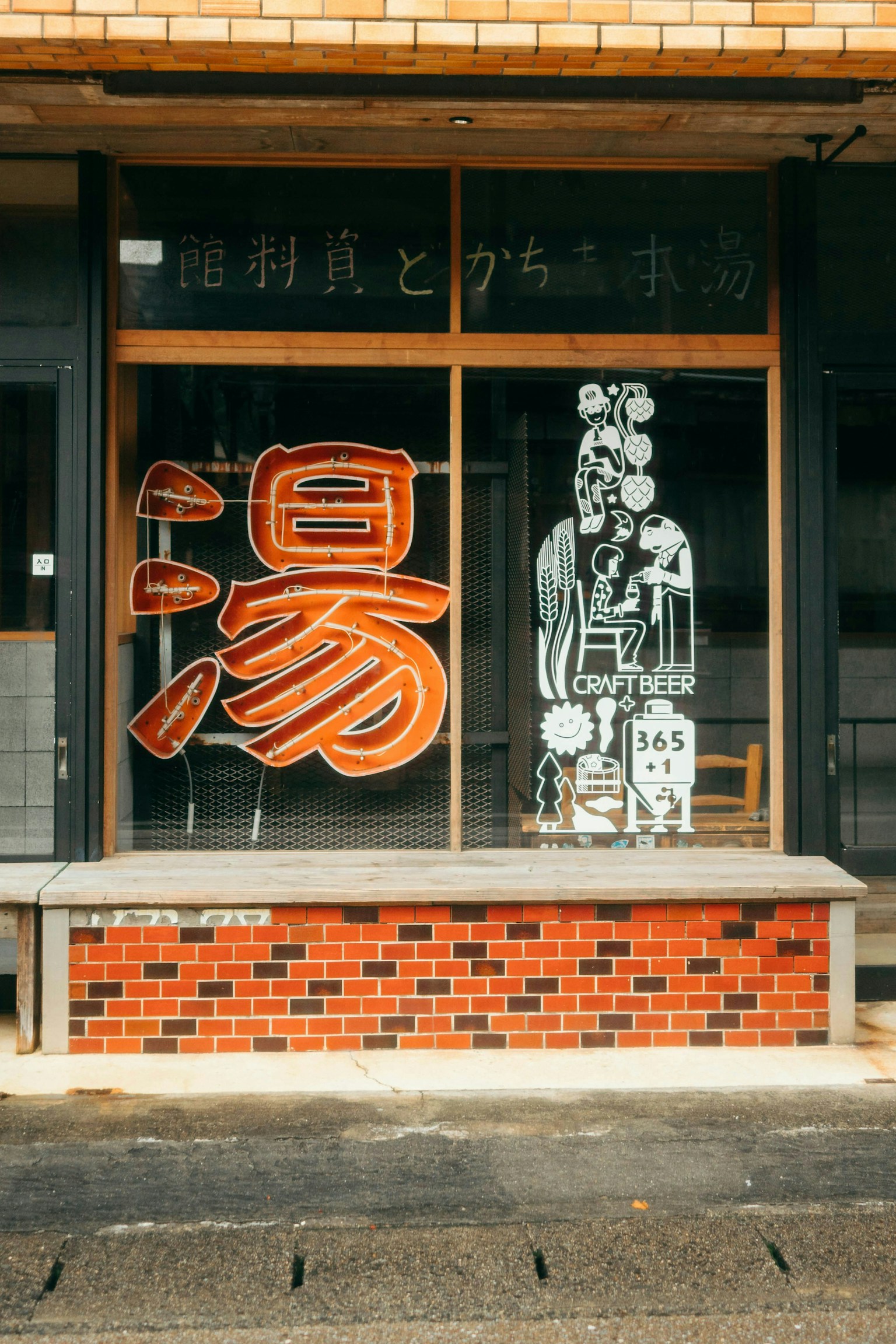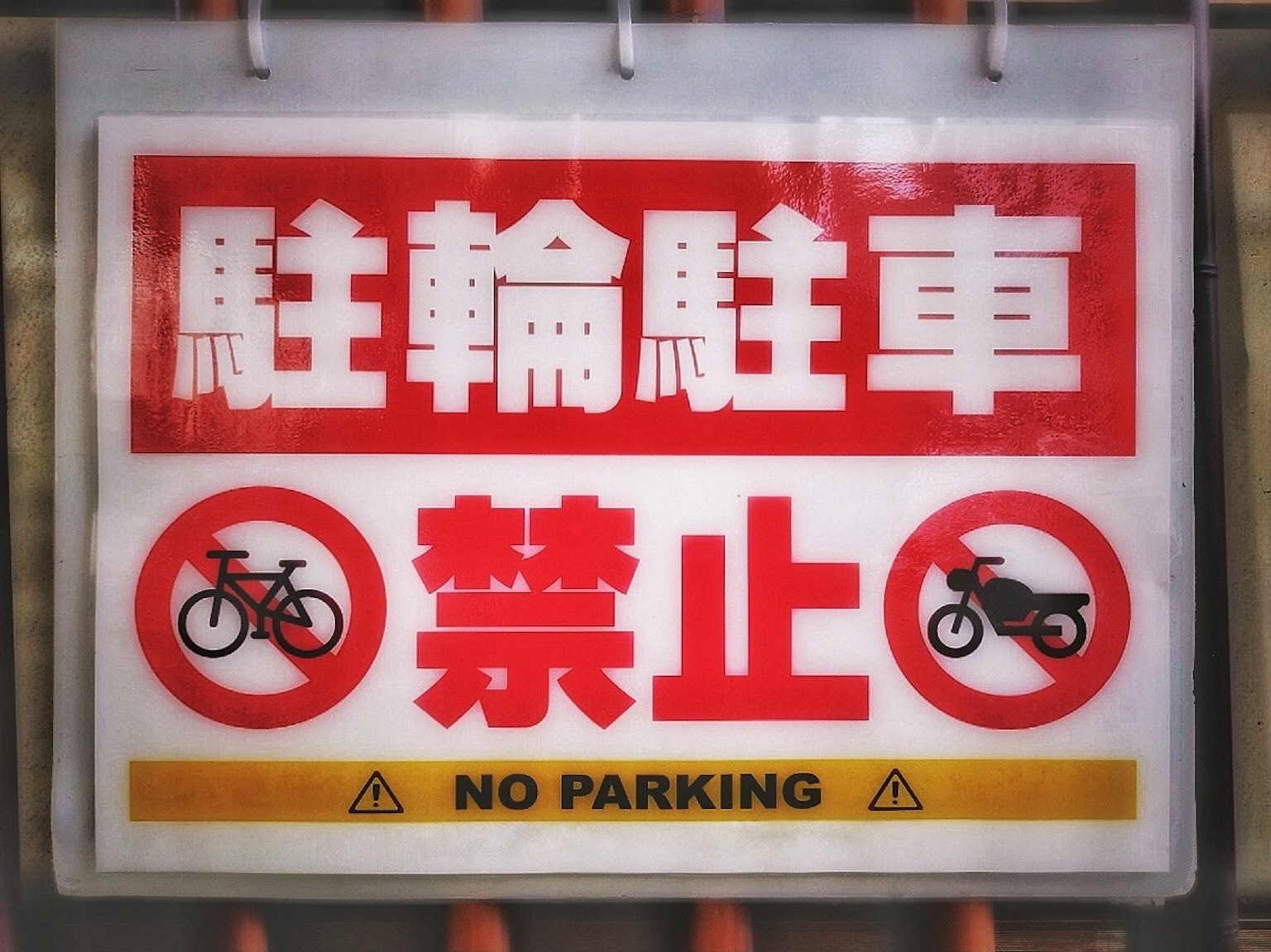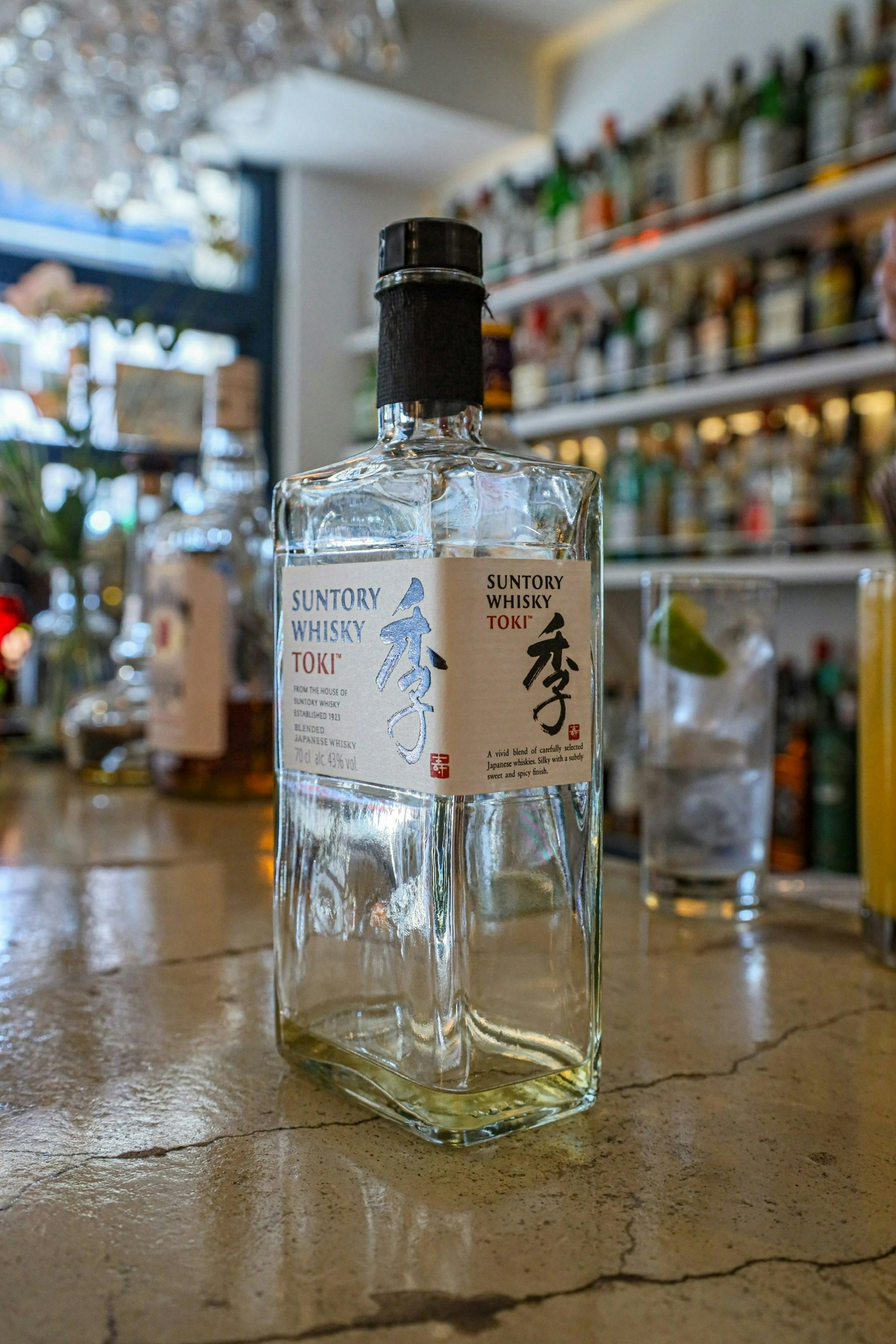
¡Hemos recibido muchas fotos que capturan expresiones en diversas fuentes!
Presentaremos algunas de las obras destacadas de esta campaña.
Elección del Editor #Font
Long Onsen
Una foto de un balneario en Nagato, Yamaguchi. La gran letra '湯' es un símbolo del onsen que parece comenzar a brillar en neón por la noche. Entre los carteles retro y el patrón de azulejos, se siente la modernidad en las letras de la cerveza artesanal, reflejando elementos turísticos.
Una foto de un cartel de prohibición de estacionamiento de bicicletas. La combinación de letras rojas llamativas y amarillo-negro de advertencia, junto con la tipografía gótica gruesa, hace que el cartel sea muy visible. Un buen ejemplo del uso de colores y fuentes apropiados para el propósito.
Una foto de una botella de whisky. El nombre de la marca '季' diseñado con pincel en la etiqueta indica claramente que es un whisky japonés. La caligrafía transmite no solo 'Japón', sino también un sentido de 'dedicación' y 'confianza'.
Para Concluir
¿Qué te ha parecido?
Incluso ahora, mientras lees esta revista, al levantar la vista, probablemente verás algún tipo de letra.
Las fuentes, a menudo fuera de nuestra conciencia diaria, pueden revelar descubrimientos ocultos si consideramos por qué se eligen.